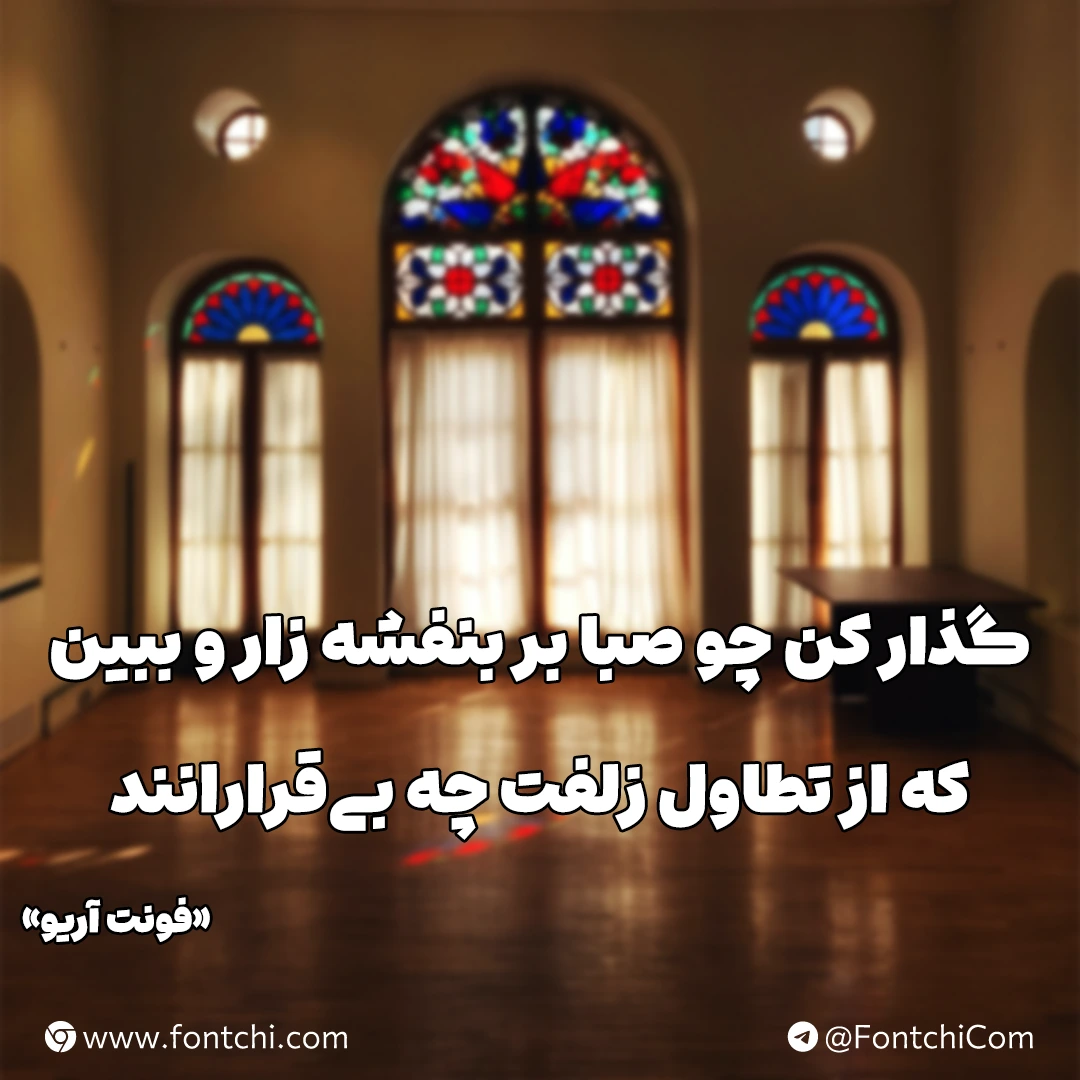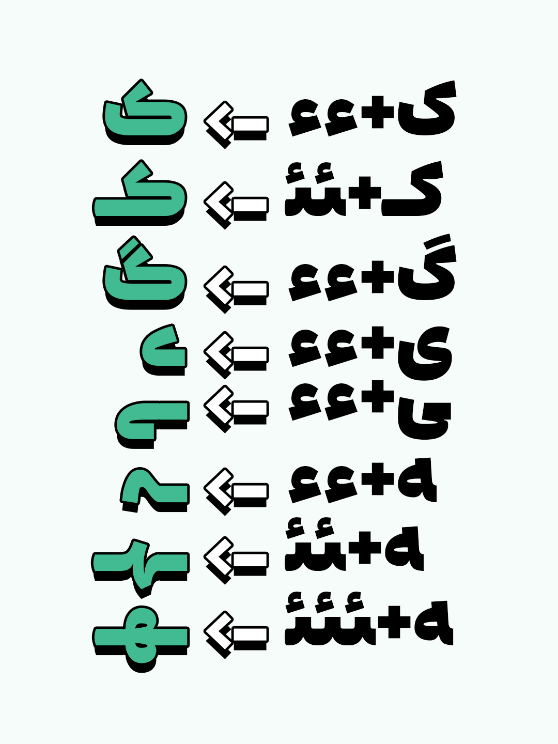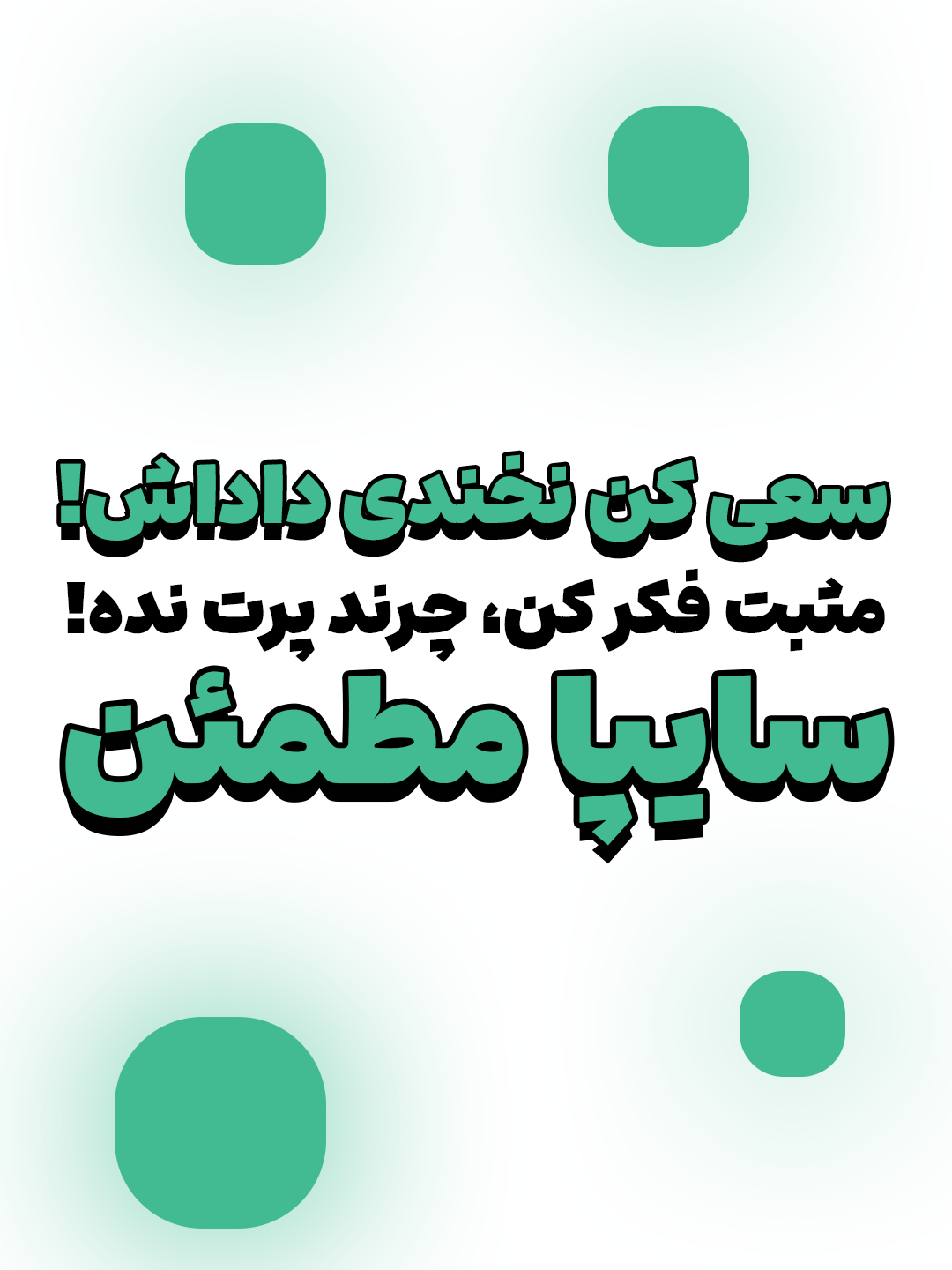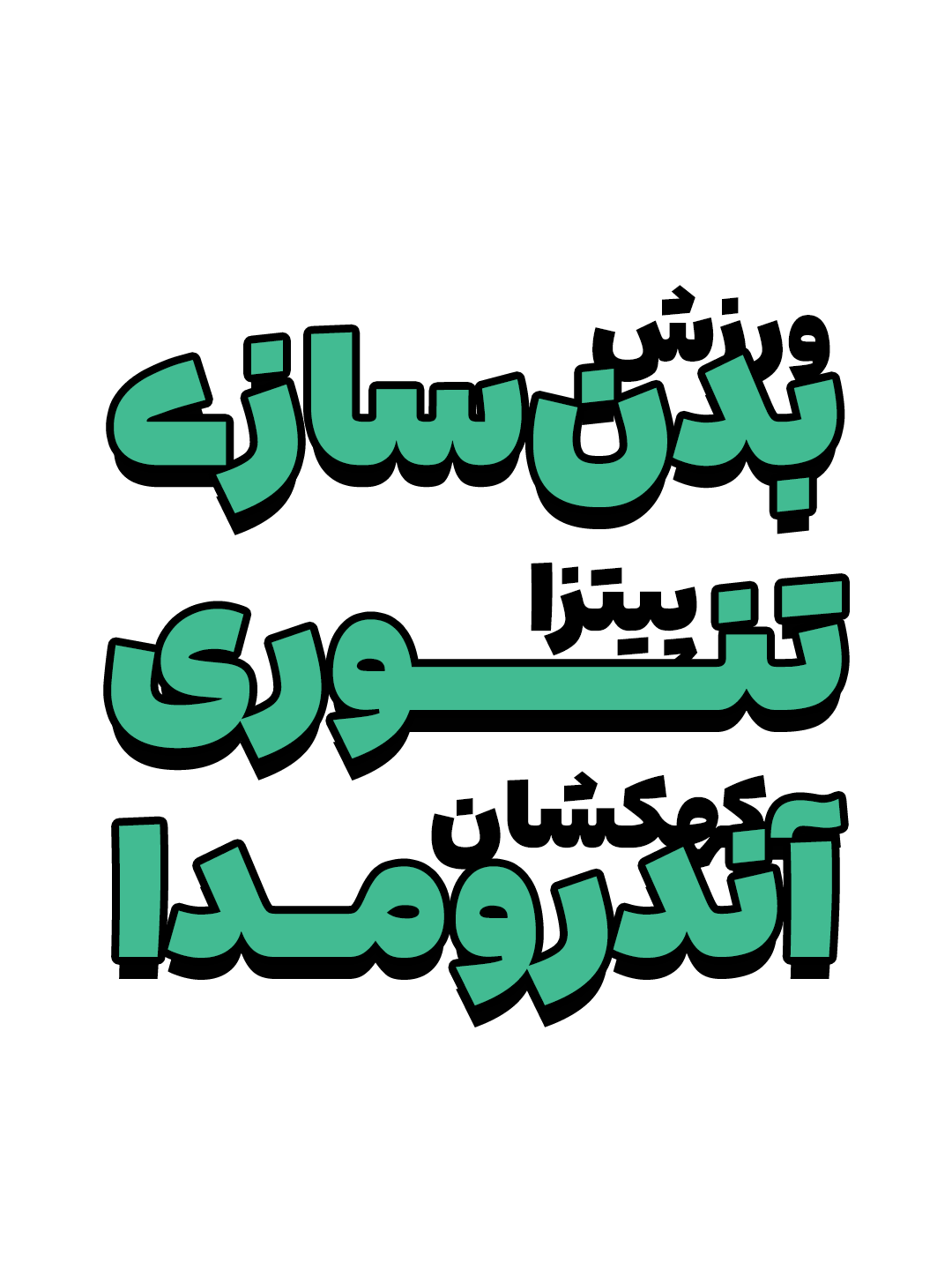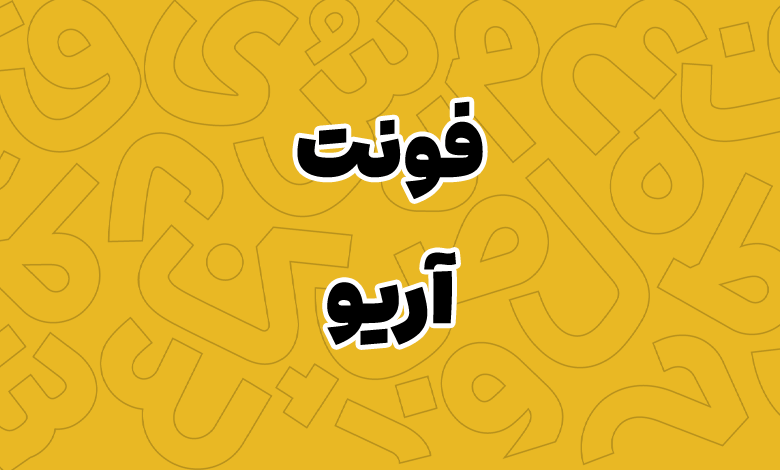
فونت آریو (Ario)
| نام | آریو |
| طراح | محمد درویشی |
فونت آریو (به انگلیسی: Ario) قلمی رایگان و مناسب برای عناوین و تیترها است که از یک وزن سنگین و سیاه پشتیبانی میکند. این فونت فارسی رایگان الهام گرفته از فونت فارسی استعداد است که با تغییراتی جزئی به صورت رایگان توسط محمد درویشی ارائه شده است.
اگر به دنبال فونتی برای تیترها و عناوین هستید که امکان استفاده از چند سبک نقطهگذاری، چینش عرضی حروف و اعداد یا حروف جایگزین را داشته باشد، میتوانید از این فونت استفاده کنید.
فونت فارسی آریو محدود به این زبان نبوده و میتوانید برای زبانهای عربی و انگلیسی نیز استفاده کنید. آریو در بسته دانلودی خود دارای ۳ ساختار مختلف است که عبارتند از:
جلد کتاب و مجلات، تامنیل شبکههای اجتماعی، عنوان نوشتههای سایت، طراحی بنرهای چاپی و پوسترهای تبلیغاتی بخشی از عمدهترین کاربردهای این فونت است. در این فونت همچنین میتوانید حروفی همچون «ک، گ، ی، ه» را با افزودن دو کاراکتر «ءء» به انتها یا میان حروف، با سبکهای متفاوتی تایپ کنید که مشابه تصویر زیر خواهند شد.